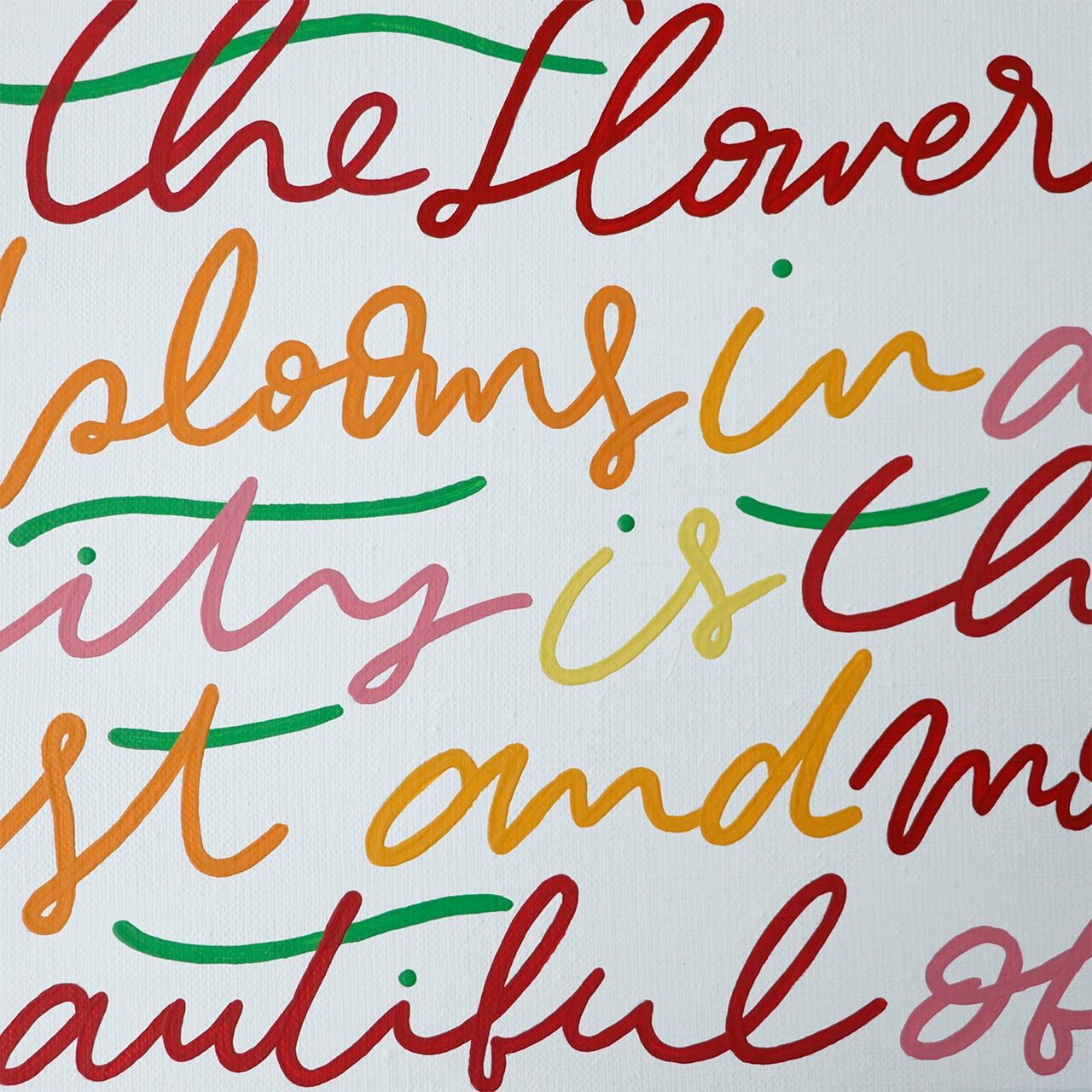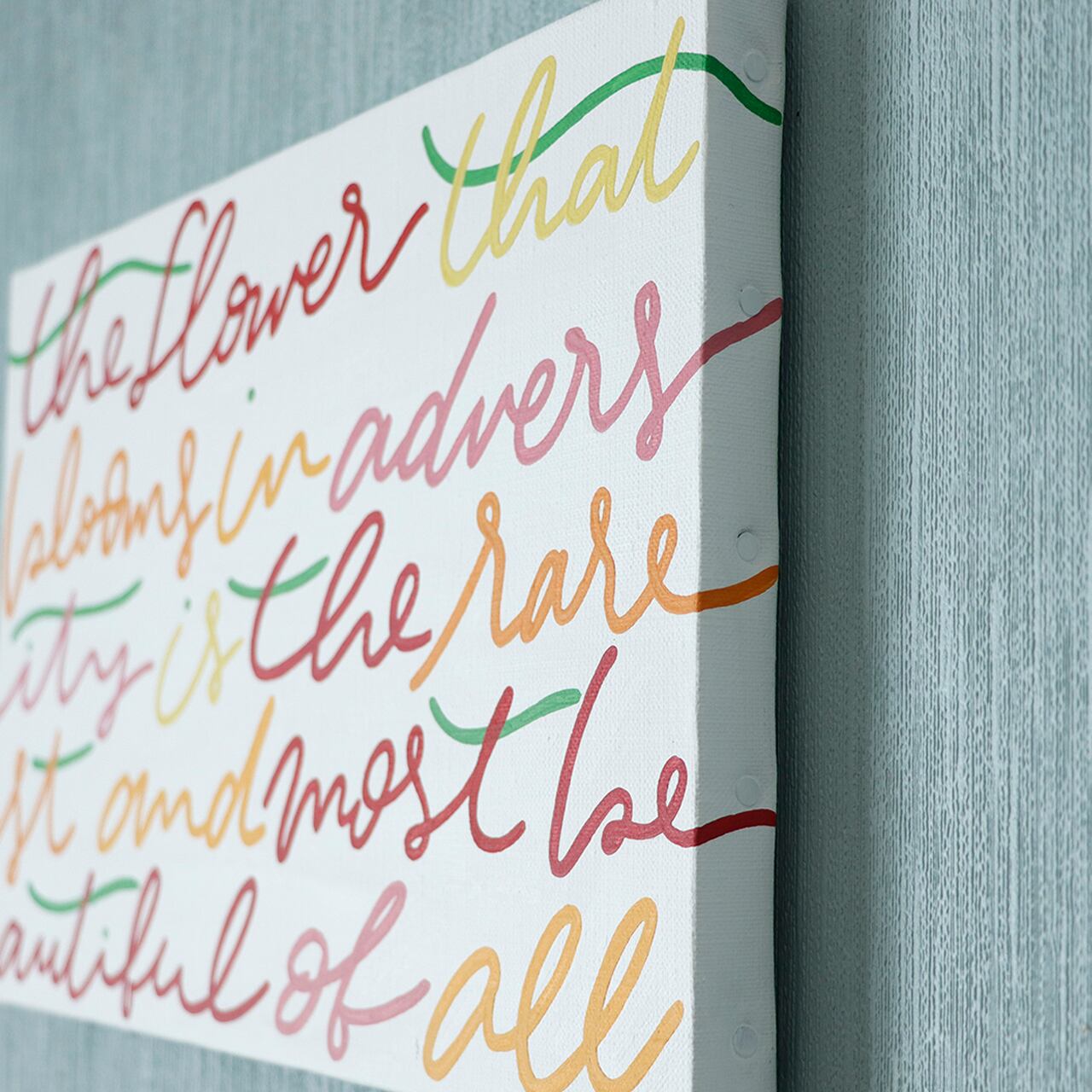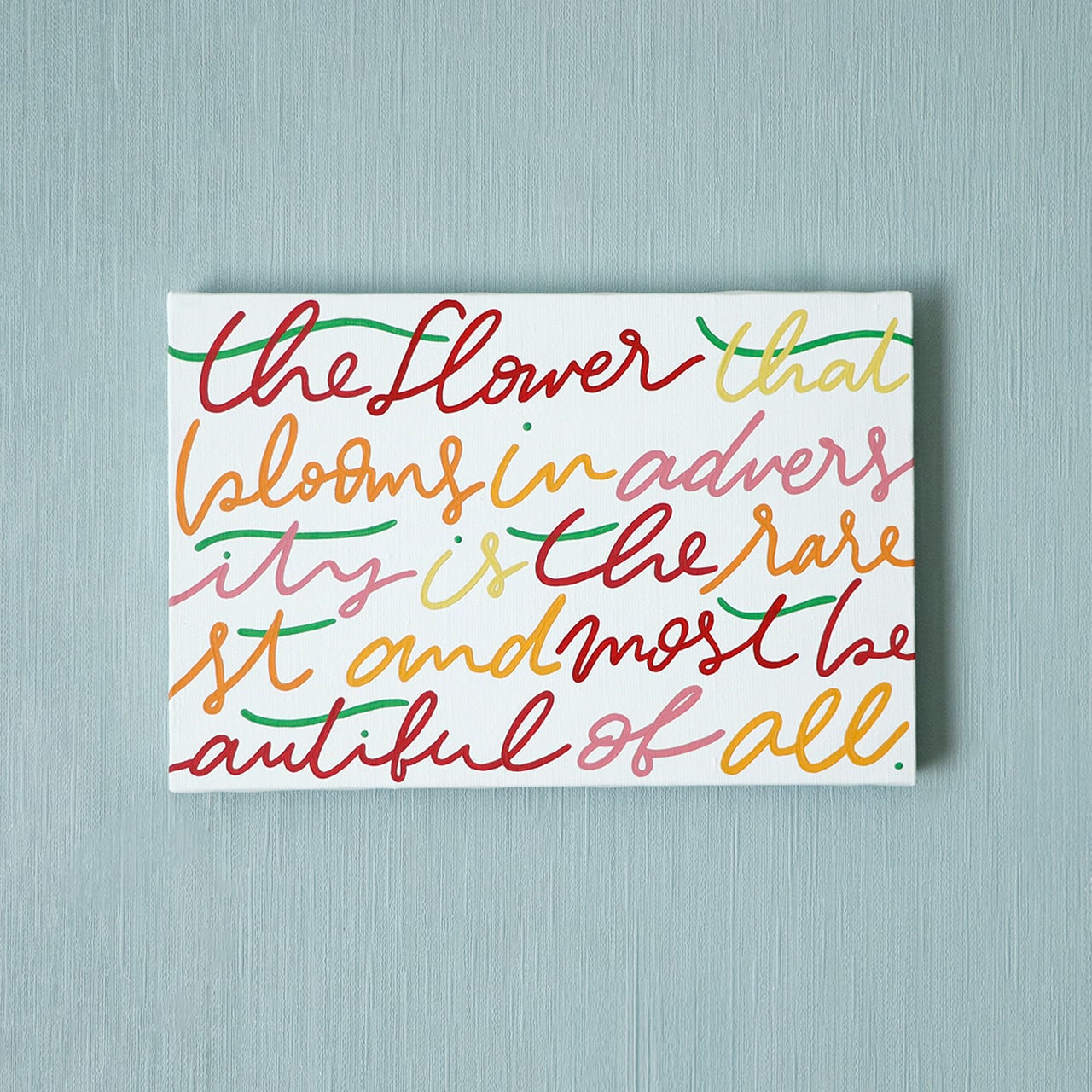
The flower that blooms in adversity is the rarest and most beautiful of all
逆境の中で咲く花は、どの花よりも貴重で美しい
世の中にはいろんな花があるように、
それぞれがたくましく自由に咲いているイメージで描きました。
文字の色は花の色、葉っぱの色を表現しています。
キャンバスをはみ出すくらい、のびのびと咲き誇りましょう◎